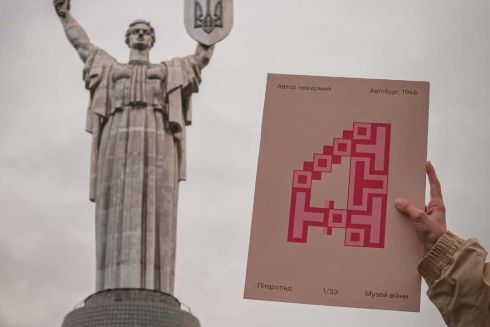
Музей війни вперше покаже рідкісні шрифти зі своїх фондів онлайн
Музей війни став учасником всеукраїнського культурно-освітнього марафону «Літеропад», мета якого – дослідження та популяризація української кирилиці. Вперше в межах цього проєкту державна культурна установа представить зразки української кирилиці зі своїх музейних фондів.
Протягом листопада на сторінці музею в інстаграмі будуть публікуватися зображення літер української абетки, взяті з обкладинок книжок, журналів і документів минулого століття.
Музей також функціонуватиме як освітній майданчик, де проводитимуться зустрічі та лекції з українськими дизайнерами, шрифторобами й дослідниками типографіки. Планується обговорення еволюції української кирилиці, її ролі у формуванні національної ідентичності, типографічних тенденцій ХХ століття та сучасного відродження шрифтової культури.
«Літеропад» — всеукраїнський культурно-освітній марафон, що об'єднує дизайнерів, митців і дослідників для популяризації української писемності та шрифтової спадщини.